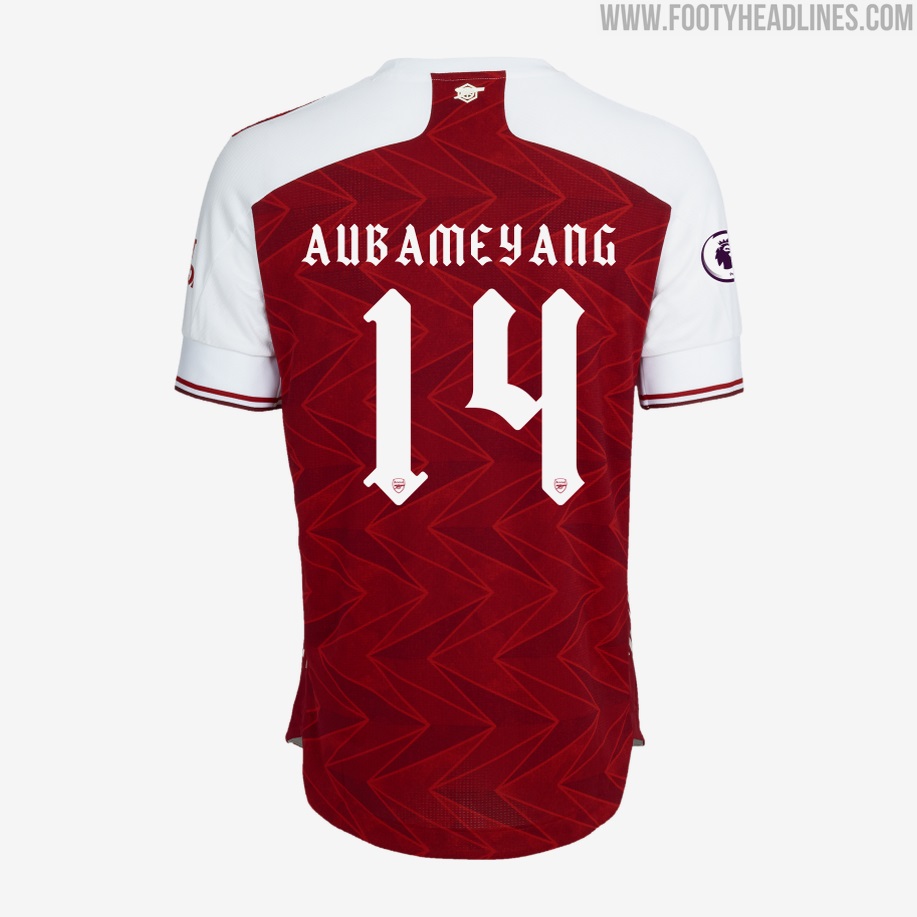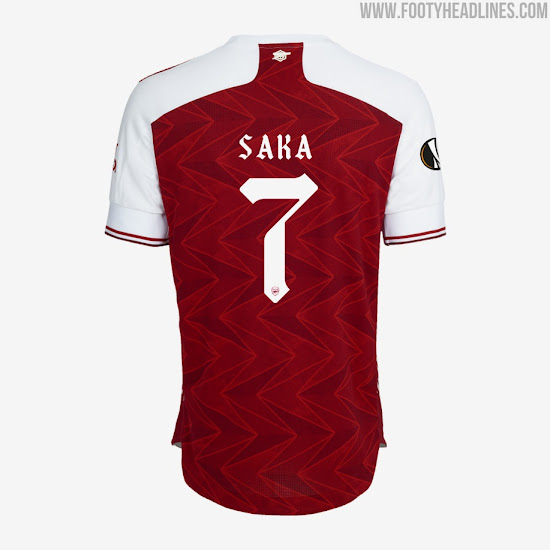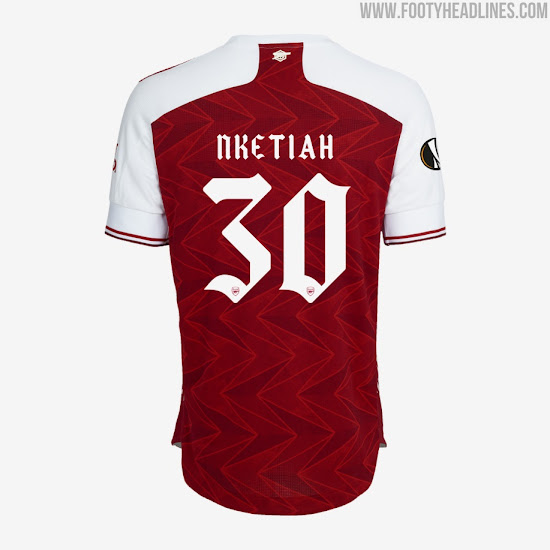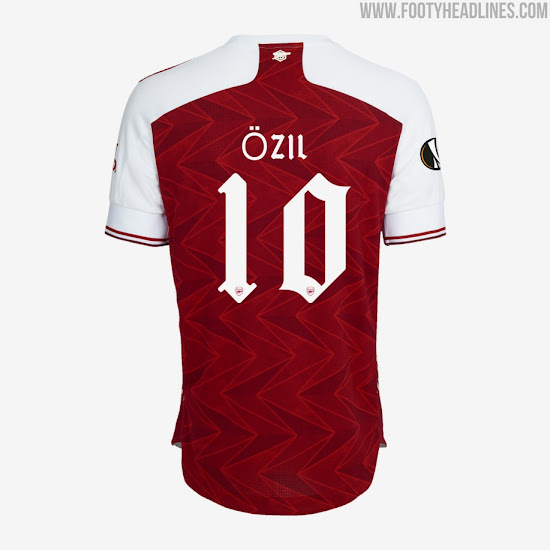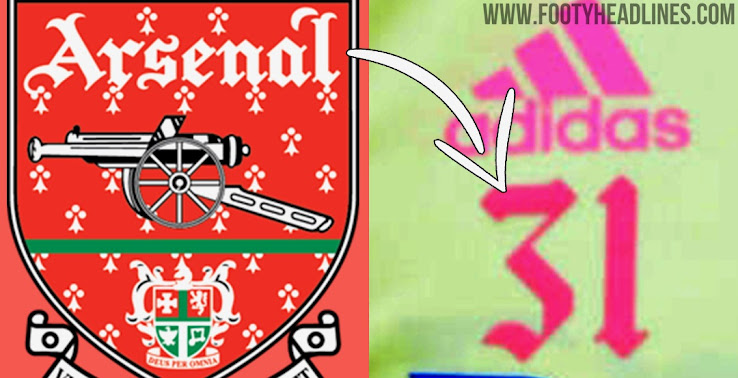
Inspiriert vom alten Arsenal-Logo - Einzigartige Adidas Arsenal 20-21 Trikot-Schriftart veröffentlicht
Premier League Klub Arsenal hat gestern nicht nur sein neues 2020-21 Heimtrikot, sondern auch seine neue, einzigartige Trikot-Schriftart vorgestellt. Die Arsenal 2020-2021 Trikot-Schriftart wurde von Adidas erstellt.
Die neue, maßgeschneiderte Arsenal FC 2020-21 Schriftart wird im FA Cup 2019-2020 Finale zusammen mit dem neuen Trikot debütiert. Sie war als erstes auf der 2020-2021 Trainingskollektion des Klubs zu sehen.
Adidas Arsenal 20-21 Trikot-Schriftart
Die Namen und Nummern des Adidas Arsenal 20-21 Trikots sind völlig anders als zuvor. Die Adidas Arsenal 2020-2021 Schriftart hat einen sehr klassischen Ansatz, der direkt vom alten Wappen des Arsenal FC inspiriert ist, das von 1949 bis Anfang 2002 verwendet wurde.
Die neue, maßgeschneiderte Arsenal FC 2020-21 Schrift wird in der Saison 2020/21 in allen nationalen und internationalen Pokalwettbewerben zum Einsatz kommen.
Premier League VersionArsenal wird die Standard-Schriftart in der Premier League verwenden, wie immer. Die Nummern auf den Hosen werden rot sein.
Arsenal 2019-2020 Pokal Trikot-Schriftart
Die Schriftart für das Adidas Arsenal 20-21 Trikot wurde zusammen mit dem Heimtrikot veröffentlicht.